衡水体
衡水体最近火了,源于一种英文书写风格,作文中英文的书写极其精细、美观、工整,可以称得上是印刷体。据说这种书写风格深的高考阅卷老师的喜爱。就像古代的馆阁体,具体是衡水一中教的一种书写法,江湖人称衡水体,据说在高考中可以得高分。
馆阁体,是清帝国朝廷公文的标准楷书书体,强调书写字形、大小、粗细的统一,字体乌黑、方正、光洁。清帝国科举也要求以馆阁体书写,不以标准馆阁体书写者无法进入翰林院。馆阁体对书写者的书法水平有着很高的要求,但也因其呆板而受到诟病。台阁体的形成是在明朝初年,书法家沈度的楷书清秀婉丽,深受明成祖喜爱,并誉为“我朝王羲之”[1]。朝廷的重要典籍皆委任沈度书写,于是当时的读书人纷纷效仿以迎合帝王的喜好。甚至当时的“台阁重臣”如杨士奇、杨荣、杨溥为皇帝起草昭告时,亦采用这种字体,号称“博大昌明体”,因为他们位居台阁,这种书体亦称为“台阁体”。到了清帝国康熙、乾隆年间,明帝国的台阁体演变成以乌黑,方正,光泽,大小如一为特征之馆阁体。由于清帝国殿试是不用誊录,评卷关键往往在应试者的书法,甚至到了“抑文重字”的程度。因此,科举制度可以说是馆阁体形成的催化剂。以书法发展史来看,馆阁体的产生是配合时代的需要,其艺术性是无法超越在唐代已发展至极致的楷书。 但是,它的方正,大小如一之规律性特征,却对中国书法普及化有一定程度之贡献。
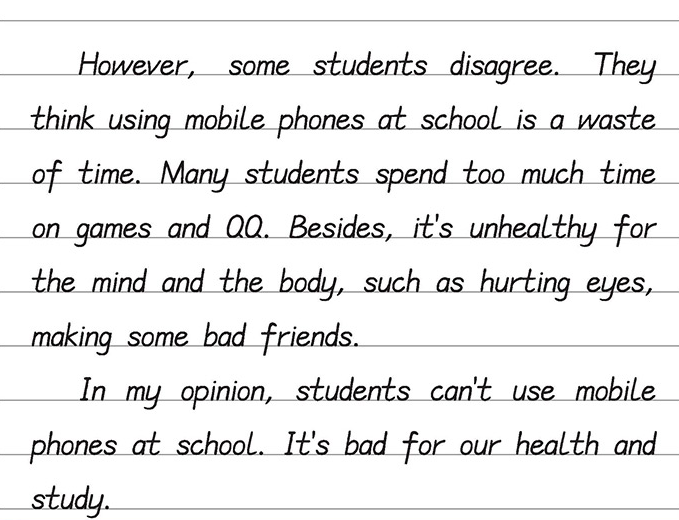
在社会对衡水体的价值观和认同度不能改变的情况下,让学生练习衡水体其实也是无可厚非的,是顺应应试教育的需求,为了高考作文得高分,衡水体是必备的工具,因为衡水体是高考制度催生出来的。但是从另外一个方面,则应该让当代教育更多地重视培养学生创造性思维,而不是仅仅为了机械地考取高分,这才是当代教育工作者真正应该关心和重视的问题!
衡水体有市场,本质上是对常规高考阅卷方式的迎合。阅卷着高度压力之下也有对阅卷速度的要求,他们通常重点看看文章开头和结尾。因此作文外观整洁美观,才有可能多看几眼,作文才有可能获得一个相对理想的分数,所以衡水体迎合了高考英语阅卷的习惯。全校英语得分占了便宜,作文外观与整洁程度雷同,他们看到其他学校考生书写的具有个人风格的作文字体,不禁会产生厌烦的感觉,得分上也就会被相对应地压低。前段时间笔者在逛书店的时候,偶然间发现了一套由电子科技大学出版社出版,马智慧老师主编的《学习型字帖英语规范书写教程》的衡水体字帖,内心感触非常深刻。在思考到衡水体弊端的同时,回归到现状也深深地意识到用分数作为量化评价标准的应试教育在未来很长一段时间依然不可被替代。